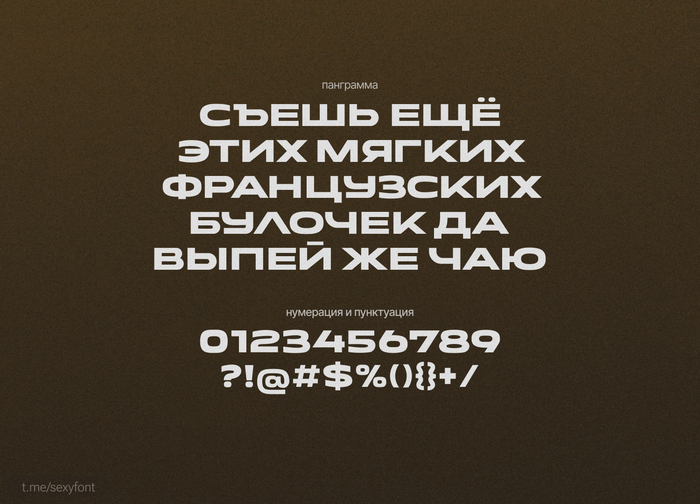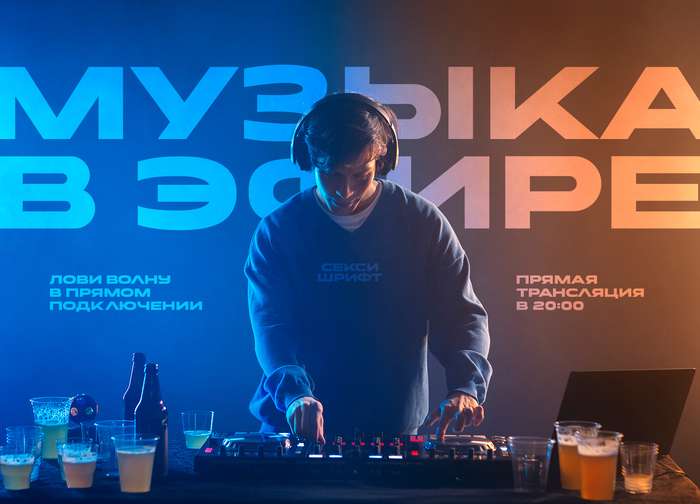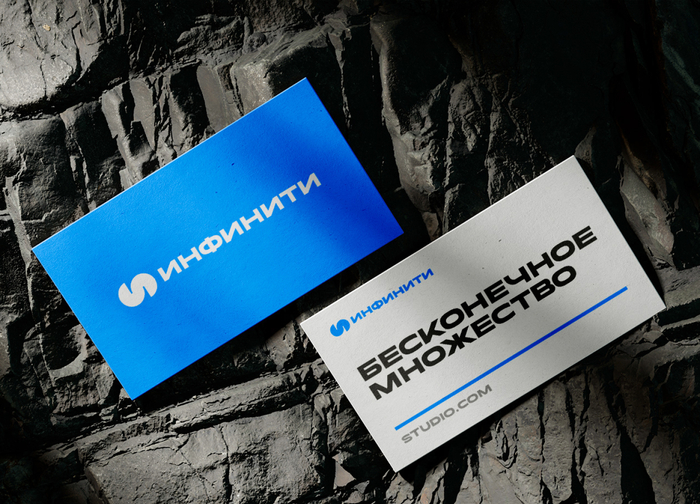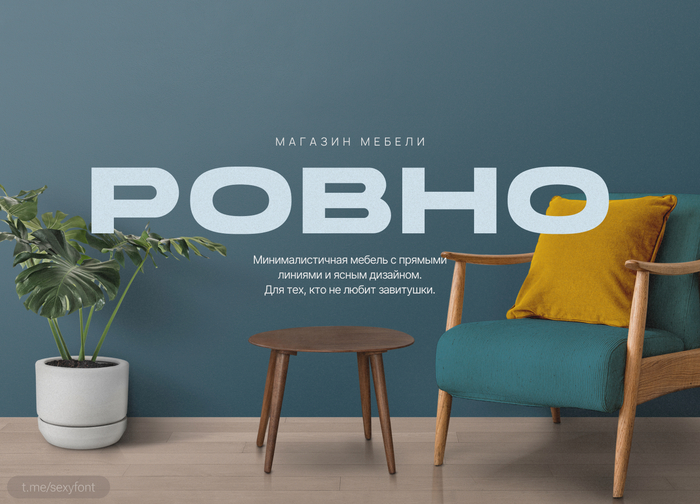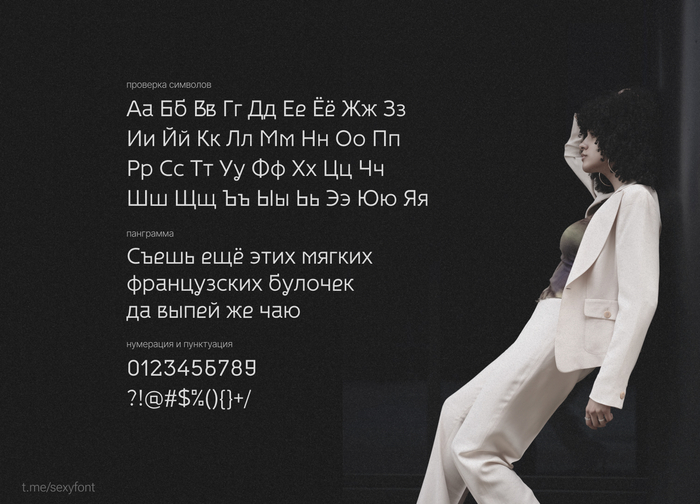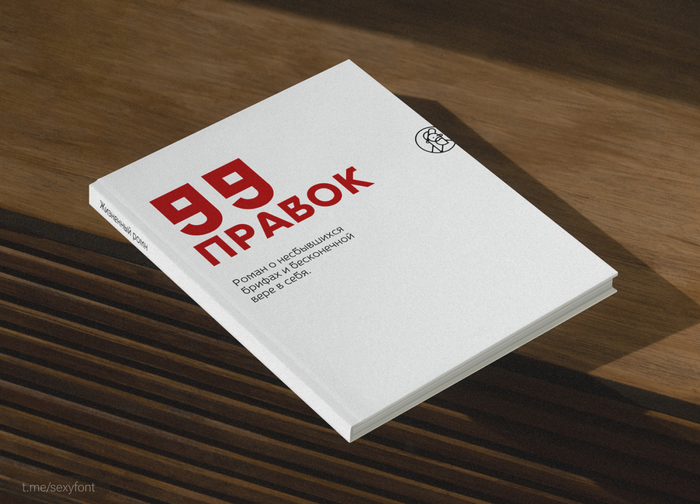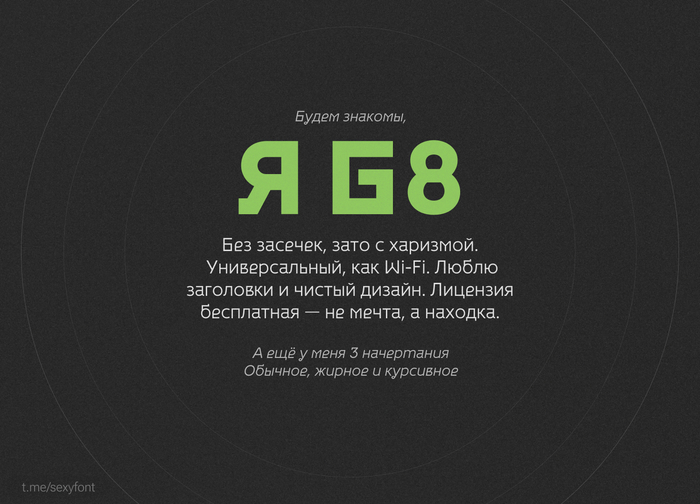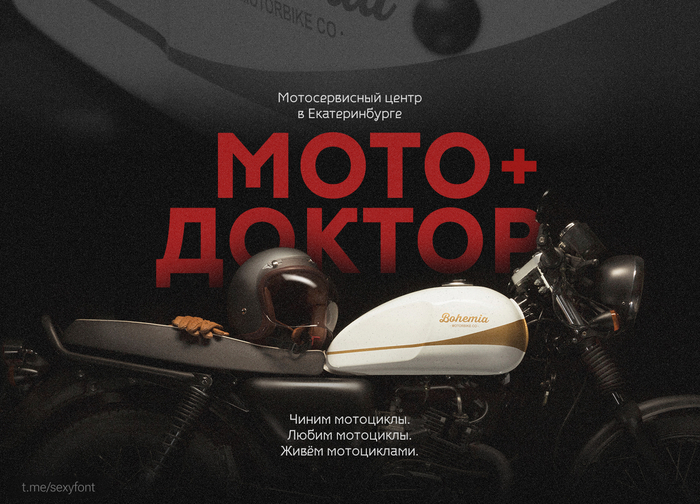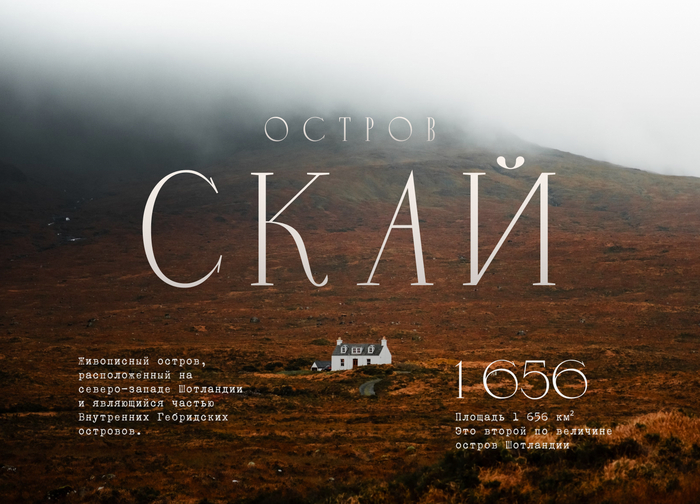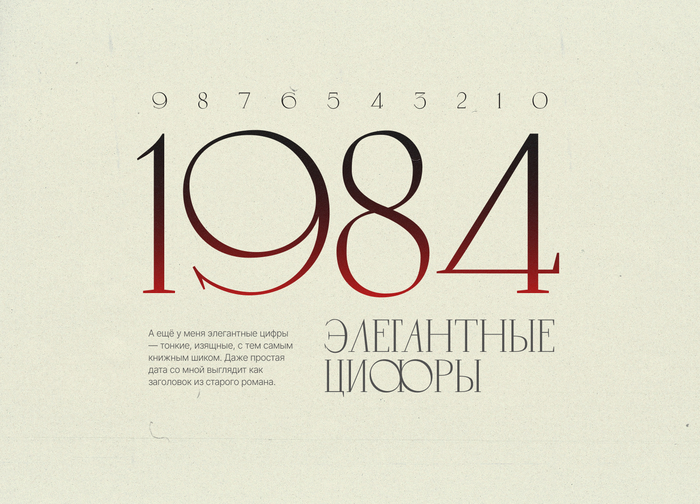
Шрифт G8
Привет, я G8.
Я — минималист, но не скучный.
Меня легко читать, трудно забыть.
Люблю заголовки, логотипы и чистый дизайн.
Говорю на 29 языках и подхожу для любого проекта.
Здравствуйте, я — Novelist
Во мне живёт дух книги и искусство буквы. Я — элегантный, с утончёнными засечками и характером, вдохновлённым классикой 60-х. Меня любят за литературную атмосферу и тонкий стиль.Хочу быть на страницах, где важен смысл, форма и вкус. И да — у меня шикарные цифры.Меня создала: Alena Krachkovskaya
Эй, я — шрифт Parajanov
Я не для скучных текстов. Я яркий, смелый и с характером. Мои формы — это смесь старого и нового, для тех, кто хочет выделяться. Подойду, если нужно что-то выразительное и нестандартное.
Шрифт Minsk
Шрифт Minsk — современный шрифт без засечек, с чистыми и прямыми линиями. Он выглядит стильно и просто, подходит для логотипов, заголовков и плакатов. Отличный выбор для проектов, где нужна ясность и минимализм.
Внутри есть 2 варианта начертаний. Одно обычное, другое максимально смелое и плохо читаемое) Но можно сочетать.
Шрифт Soyuz grotesk
Вы можете его любить или ненавидеть) Но он определенно войдет в историю. Последние пару-тройку лет он везде. Но меня все равно часто спрашивают: «А что это за шрифт?»
Шрифт разработан студентами Московского института печати в 1963 году, Юрием Курбатовым и Максимом Жуковым. Поскольку Helvetica в кириллическом варианте тогда не существовала, они решили сделать свою домашнюю копию. Автор — The Temporary State. На нашем канале он появился впервые уже в конце 2022.
Шрифт, как со старых холодильников
Kholodos! Еще один шрифт плюсом!) Примерно такие использовали в дизайне старых холодильников) Олды должны помнить. Может у кого даже примеры найдутся?
Шрифт Oktyabrina Script
Новая презентация! Oktyabrina Script — декоративный рукописный шрифт, созданный дизайнером Александрой Гофманн. Шрифт, который не просто пишет, а заявляет! Немного пионерский характер)